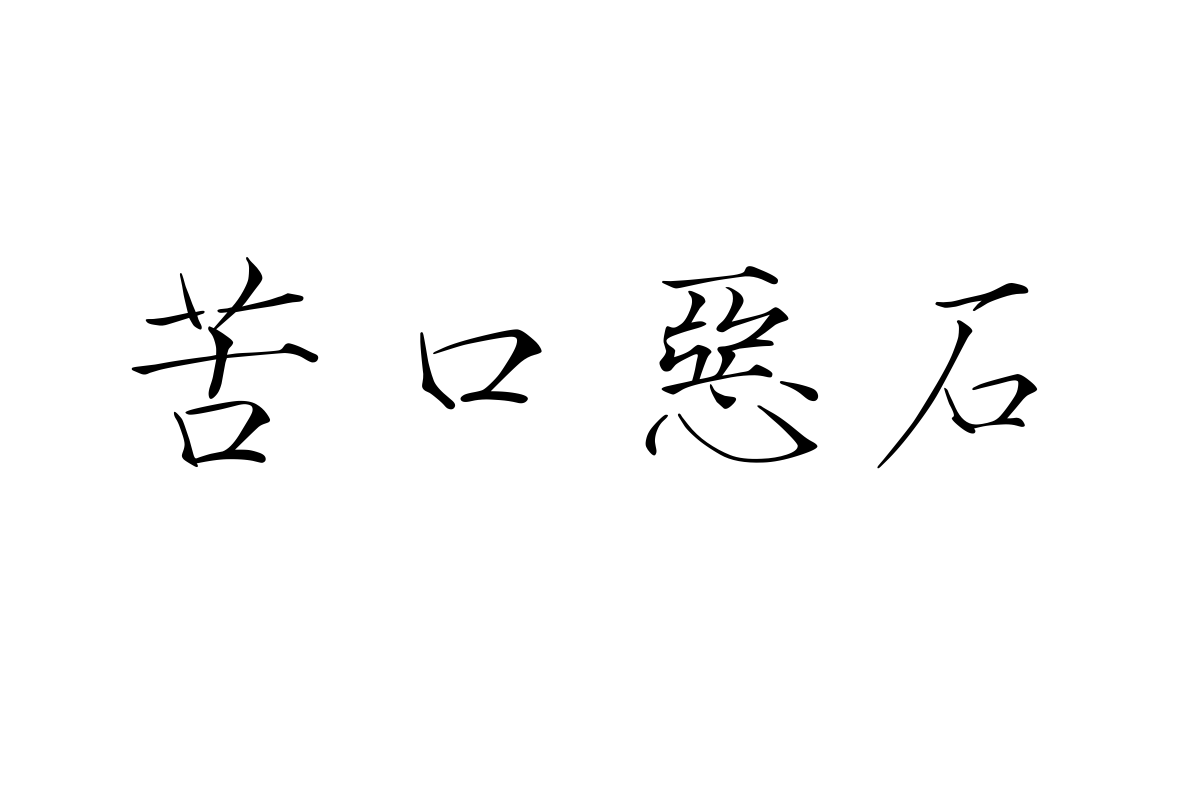
汉仪瘦金书是一种具有独特风格的汉字字体,它源自古代中国,以其独特的笔画结构和艺术美感而著称。这种字体的特点是笔画纤细、流畅,给人一种优雅、精致的感觉。
汉仪瘦金书的笔画粗细变化丰富,线条柔美,给人以美的享受。它的笔画结构紧凑,但又不失灵动,使得整个字体看起来既有力度又充满了艺术感。此外,汉仪瘦金书还注重字与字之间的间距和布局,使得整体效果既和谐又有层次感。
总的来说,汉仪瘦金书是一种非常适合用于设计海报、杂志、广告等视觉传达领域的字体。它不仅能够提升设计的美感,还能够增强信息的传递效果,让观者在欣赏作品的同时,也能感受到作者对美的追求和对艺术的理解。